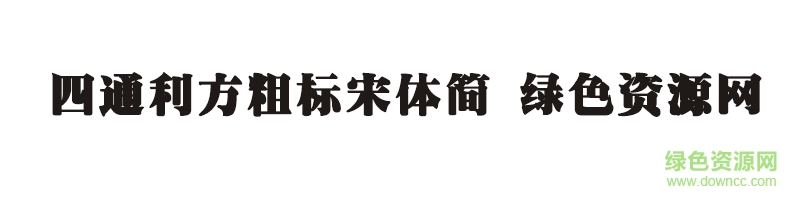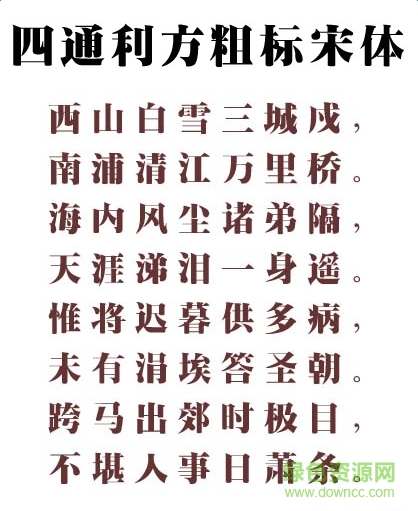
四通利方粗標(biāo)宋體簡是四通利方字體中常用于寫標(biāo)題的字體素材,字體恢弘大氣,橫豎比例一致,非常吸引人眼球。此次字體適用范圍特別廣泛,用戶各行各業(yè),如果你有需要的話,歡迎來下載!
四通利方粗標(biāo)宋體簡是四通利方字體庫中的一種字體,字體秀麗頎長、風(fēng)姿翩翩,可應(yīng)用于繪畫設(shè)計、文學(xué)創(chuàng)作、平面廣告、印刷包裝等領(lǐng)域。四通利方粗標(biāo)宋體簡適用于報紙大標(biāo)題和書籍、畫報的美術(shù)裝幀和廣告用字等,字體莊重,橫豎比例一致,引人注目。四通利方粗標(biāo)宋體字體粗重平穩(wěn),橫豎比例一致,構(gòu)體莊重,引人注目,適用于報紙大標(biāo)題及書籍、畫報的美術(shù)裝幀和廣告用字。